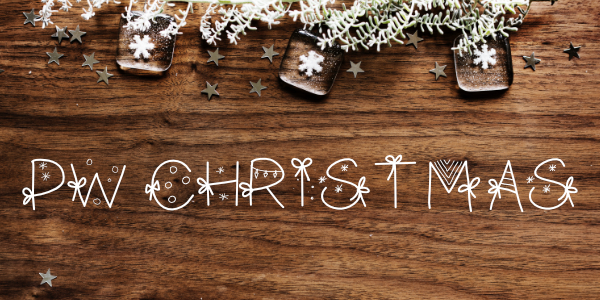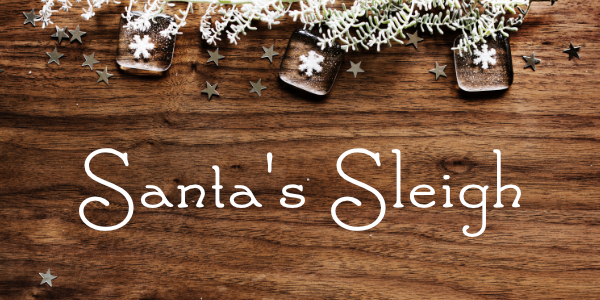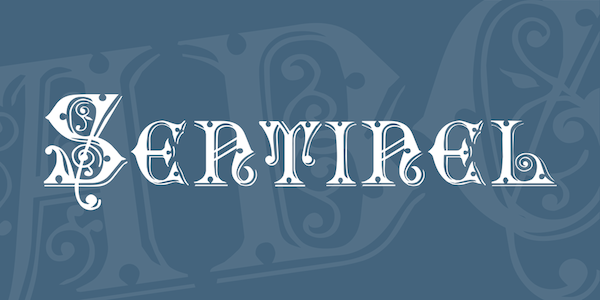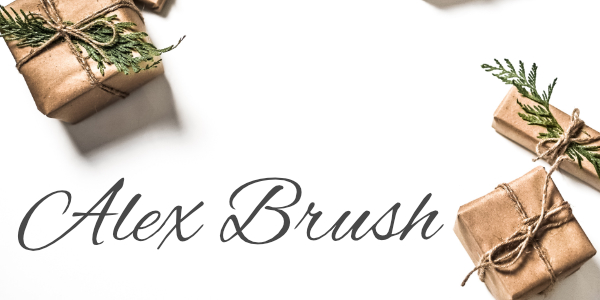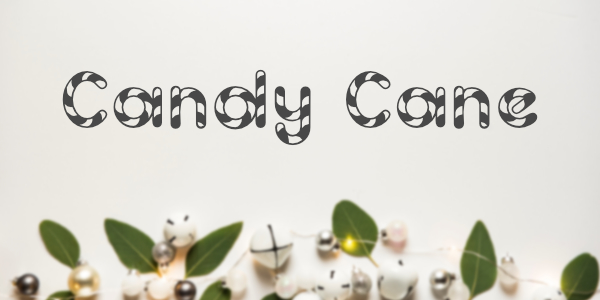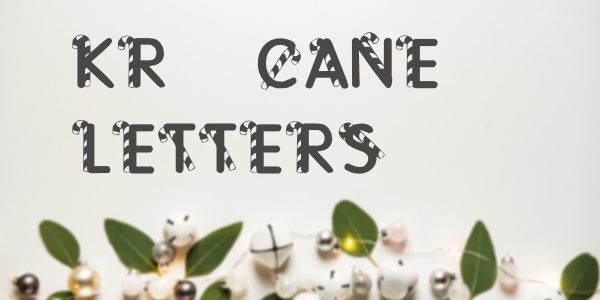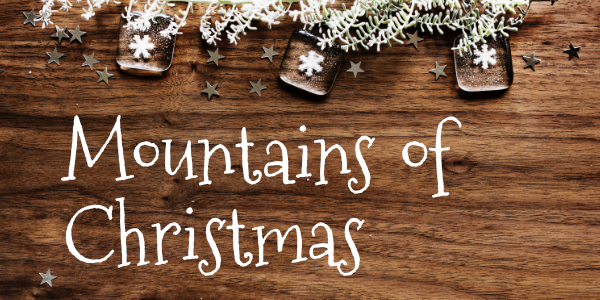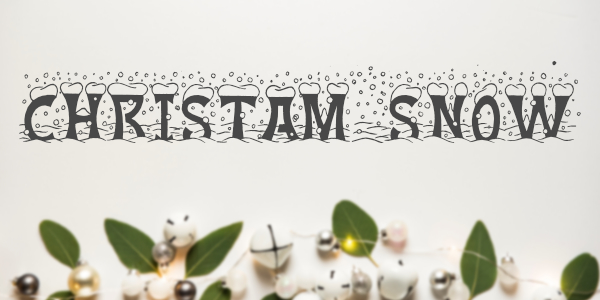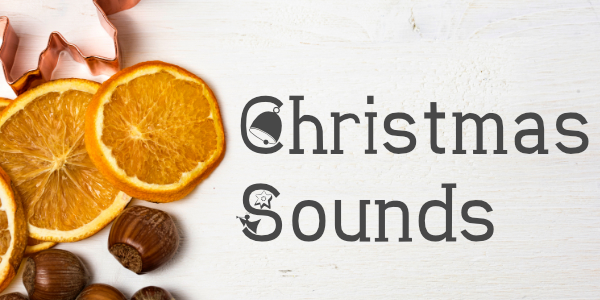
25 typographies de Noël à télécharger gratuitement
Pour harmoniser vos visuels avec l’esprit de Noël rien de mieux que d’utiliser des polices d’écritures adaptées.
Je vous propose aujourd’hui une sélection de 25 typographies (gratuites évidemment) spécialement dédiées à Noël pour parfaire vos créations à l’approche des fêtes de fin d’année.
1. Snowhouse
Typo noel Snowhouse
2. I Love Christmas
I Love Christmas
3. One Starry Night
One Starry Night
4. Frosty
Typo Frosty
5. Mountains of Christmas
Mountains of Christmas typographie
6. Dear Santa
Typo Dear Santa
7. Maratre
Typo Noel Maratre
8. Santa’s Sleigh
Typo sant Sleigh
9. Merry Christmas
Merry Christmas
10. KR Cane Letters
KR Cane Letters
11. Nickelodeon
Typo Noël Nickelodeon
12. Sentinel
Typo noel Sentinel
13. Candy Cane
Candy Cane
14. PW Christmas
15. Alex Brush
Alex Brush
16. Chopin Script
Chopin Script
17. Christmas Sounds
Christmas Sounds
18. Kingthings Christmas
Typo Kingthings
19. Harrington
Typo Noel Harrington
20. Stackyard
Stackyard typo
21. Harbell